行书字体特点是端正平稳,放纵流动,行书在书写的时候点画的主要写法是露锋入纸,字体以欤侧代替平整,比较复杂的笔画变的更加的简单省略,点画之间的呼应是用勾、挑、牵丝来进行加强的,用圆转的笔画代替了方折的笔画。
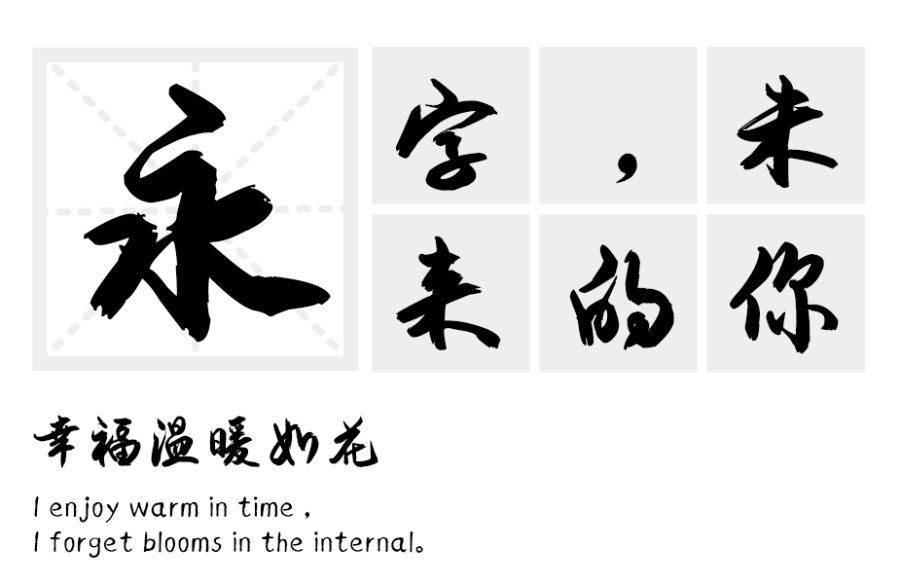
行书特点如下
1,用笔特点
行书是介于楷、草du间的一种书体。写得比较zhi放纵流动,近于草书的称行草;写dao得比较端正平稳,近于楷书的称行楷。
在书写过程中,笔毫的使转,在点画的各种形态上都表现得较为明显,这种笔毫的运动往往在点画之间,字与字之间留下了相互牵连,细若游丝的痕迹,这就是丝连。行书是楷书的快写,是楷书的流动。
经过对几组楷书与行书个字的分析,发现楷书与行书书写时,点画的写法,用笔需遵循的准则,如中锋,铺毫,逆入平出,提按起主,藏锋等都是一致的,只是行书书写时比较舒展,流动。
行书的用笔有以下几个特点:
[1]点画以露锋入纸的写法居多;
[2]以欤侧代替平整;
[3]以简省的笔画代替繁复的点画;
[4]以勾、挑、牵丝来加强点与画的呼应;
[5]以圆转代替方折;
2,结构特点
大小相兼。就是每个字呈现大小不同,存在着一个字的笔与笔相连,字与字之间的连带,既有实连,也有意连,有断有连,顾盼呼应。
收放结合。一般是线条短的为收,线条长的为放;回锋为收,侧锋为放;多数是左收右放,上收下放,但也可以互相转换,不排除左放右收,上放下收。
疏密得体。一般是上密下疏,左密右疏,内密外疏。中宫紧结,凡是框进去的留白越小越好,划圈的笔画留白也是越小越好。布局上字距紧压,行距拉开,跌扑纵跃,苍劲多姿。
浓淡相融。行书书写应轻松、活泼、迅捷,掌握好疾与迟、动与静的结合。墨色安排上应首字为浓,末字为枯。线条长细短粗,轻重适宜,浓淡相间。和草书差不多,但没那么草。